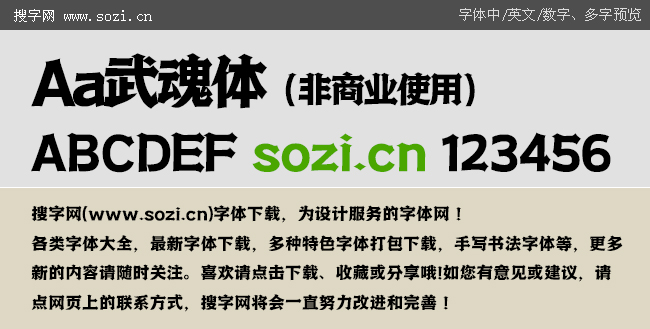
Aa武魂體
搜字網(wǎng)給大家提供一款A(yù)a武魂體(非商業(yè)使用)中文字體下載,Aa武魂體是一款醒目的藝術(shù)字體,該字體筆畫粗厚,字型工整,頓筆有力,非常醒目。適合應(yīng)用于藝術(shù)設(shè)計(jì)、平面宣傳設(shè)計(jì)、網(wǎng)頁(yè)設(shè)計(jì)、海報(bào)設(shè)計(jì)等應(yīng)用(此字體為個(gè)人非商用版,商用可以聯(lián)系QQ:1006760504)。